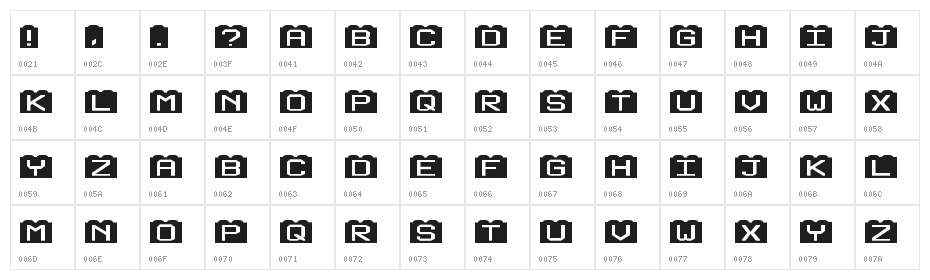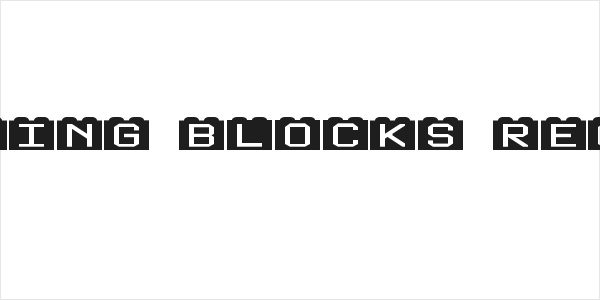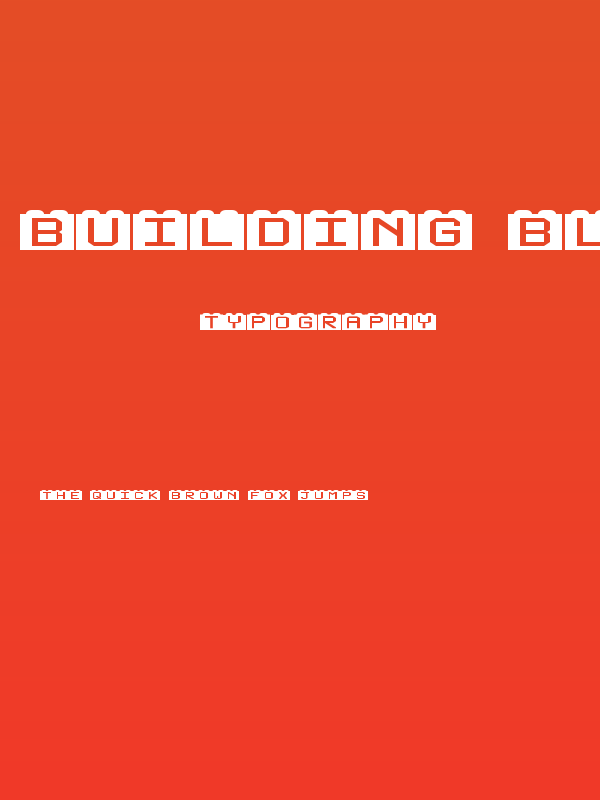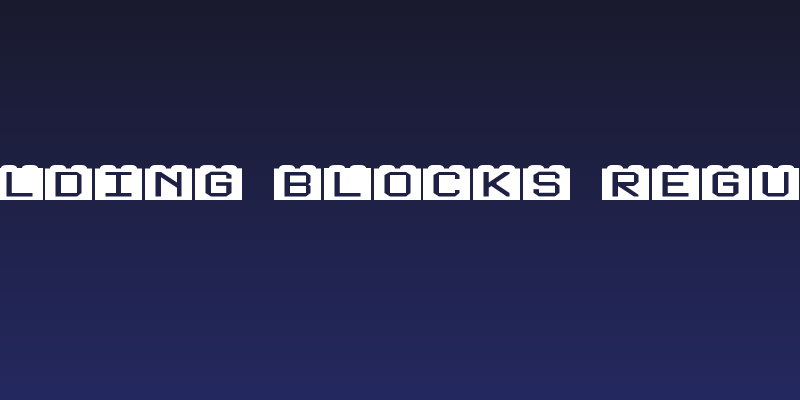
Building Blocks Regular Font
✎ Decorative
| مشاريع مقترحة | Ideal for children's educational materials, toy packaging, playful branding, and creative posters. |